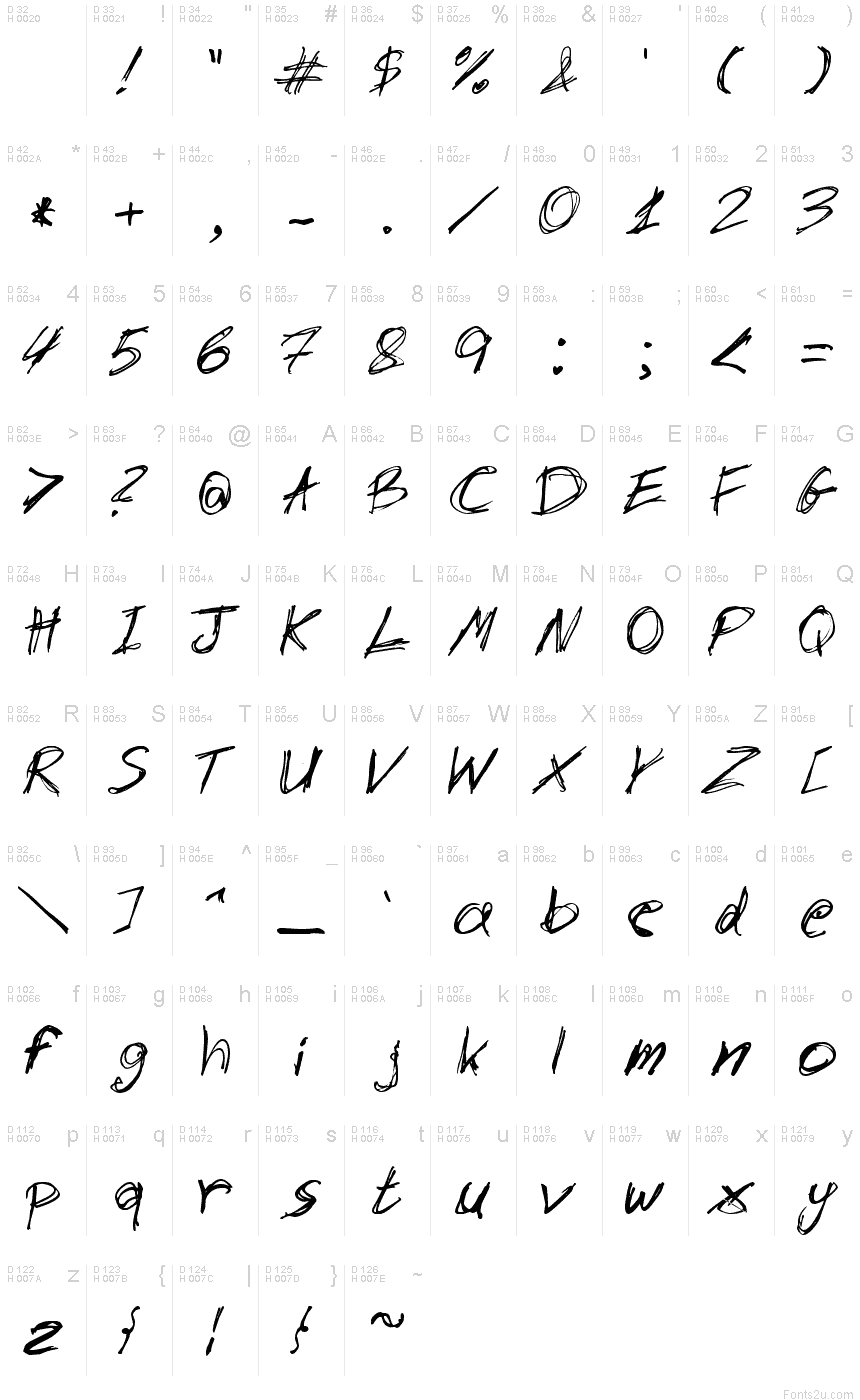
Slantorama od Veredgf je bezplatné písmo typu trash-brush script s rychlým sklonem připomínajícím graffiti. Písmena se rozlévají v napjatých smyčkách, střídají se v nich náhlé tlusté tahy a drsné, ošoupané okraje, díky čemuž celé písmo působí spíše jako čerstvá improvizace než vyleštěný design.
Skvěle se hodí na obálky zinů, grafiku pro skate a streetwear, plakáty kapel, nadpisy a titulní karty, kde vynikne syrový, ručně kreslený styl. Protože jde o bezplatné písmo, výborně poslouží i pro rychlé skici log, výrazné prvky v designu nebo krátké texty na obalech, protože jeho neklidný rytmus a nepravidelná textura odvedou kus práce za vás ještě předtím, než cokoli přidáte.